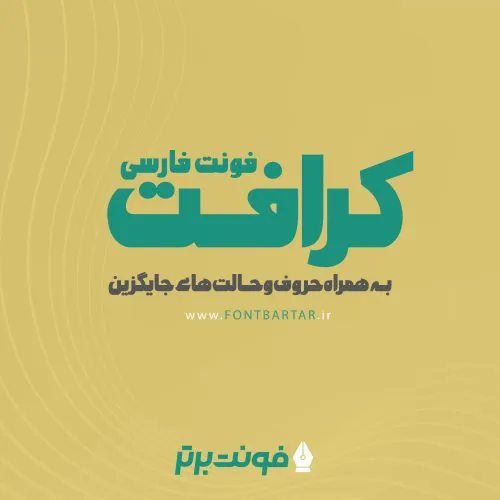
فونت کرافت
فونت کرافت مورد استفاده برای:
- طراحان وب سایت و گرافیست های خلاق می توانند از این فونت زیبا فونت در طراحی پروژه های تبلیغاتی و تجاری خود کمک بگیرند.
حروف جایگزین فونت کرافت: